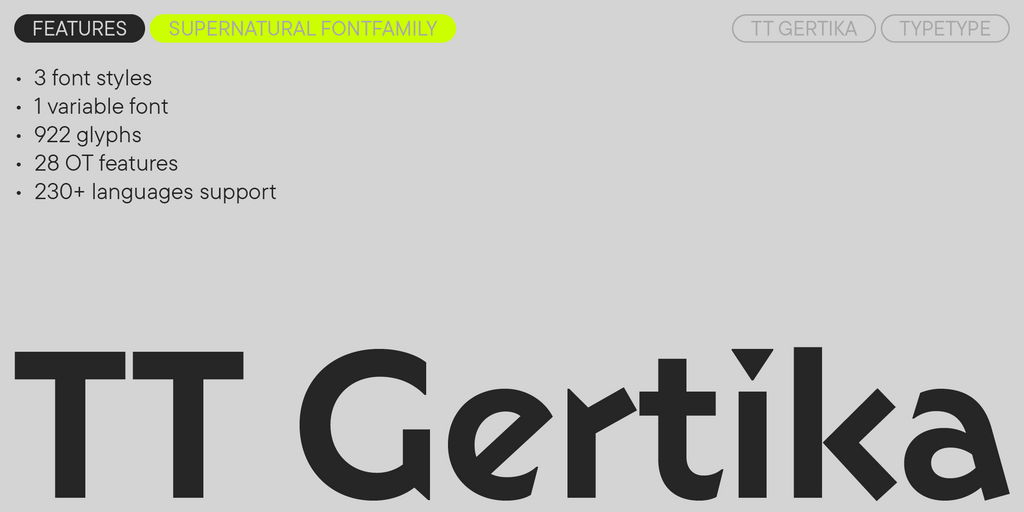
Минималистичные шрифты
TT Runs — это выразительный шрифт, который идеально впишется в проекты со спортивной тематикой. При этом гарнитура отлично подойдет и для других современных проектов: после обновления сфера ее применения значительно расширилась.
TT Turns — геометрический гротеск с акцентными круглыми знаками и выразительными нависающими элементами. Это универсальный шрифт, который лаконично выглядит и отлично читается в маленьком размере, при этом в крупных кеглях становится акцидентным и проявляет свой характер на максимум. Он энергичный, сильный и динамичный — особенно отчётливо это проявляется в наклонных начертаниях.
В TT Frantz можно найти небольшие отсылки в эстетике арт-деко, которые выражены в сильно заниженной или наоборот сильно завышенной талии у букв. Кроме того, в зависимости от положения ползунка регулировки оси, у некоторых букв изменяется закрытость апертуры.
TT Quaris — изысканная и современная ленточная антиква. Перед разработкой этой гарнитуры мы провели глубокое исследование архетипов ленточных антикв.
TT Modernoir — акцидентный гротеск с разноширинными пропорциями. Плавные линии и изящные формы ар-нуво в этом шрифте сочетаются с ритмичностью и импровизационной свободой джаза.
TT Firs Neue — скандинавский гротеск, сочетающий выразительные графические элементы с универсальностью использования. Мы проанализировали каждый контур и графический элемент. Пересобрали шрифт заново, чтобы сохранить лучшее и исправить необходимое.
TT Ramillas — стильная и современная антиква. Включает уникальные декоративные начертания и буквицы с цветочным орнаментом.
TT Paplane — акцидентный сквадраченный гротеск. Так, характерные черты этого гротеска — сквадраченные формы, 45-градусные срезы и обтекаемые внешние контуры.
TT Travels Next — сверхмодный широкий гротеск. Широкие пропорции — одна из отличительных черт этой гарнитуры: знаки почти не сужаются при переходе от толстого начертания к тонкому.
TT Firs Text создавался на основе обновленной в 2023 году гарнитуры TT Firs Neue. Мы сохранили эстетику скандинавского минимализма, но полностью перерисовали все выразительные элементы, сделав их более мягкими и традиционными.
TT Trailers — стильный и выразительный акцидентный гротеск. Его легко узнать по необычной графике: рисунок каждого знака в этом шрифте авторский, формы экспериментальные. Он гармонично смотрится в оформлении афиш и плакатов, идеально подходит для оформления титров. Однако на практике сфера применения этой гарнитуры гораздо шире.
TT Norms® Pro — один из самых востребованных шрифтов студии, выбор известных мировых брендов. Более трёх переизданий за семь лет, первые строчки на MyFonts, десятки кастомизаций. Это «рабочая лошадка», которая станет незаменимой базой любой шрифтовой коллекции.
TT Commons™ Pro — один из самых востребованных шрифтов студии. Сфера его применения практически безгранична! Беспроигрышный вариант для тех, кто ищет стильный и функциональный базовый шрифт для любых проектов.
TT Hoves Pro — скандинавский гротеск с нейтральным, но в то же время узнаваемым характером. Это удобный и функциональный, при этом стильный и эстетичный инструмент для дизайнеров. Такой шрифт позволит вам решать множество разноплановых задач!
TT Supermolot Neue — непобедимое оружие в борьбе за стиль! Это технологичный модульный гротеск с футуристическим настроением и мощным функционалом. Шрифт идеально подойдёт для оформления компьютерных игр и множества других проектов.
TT Firs Neue — сбалансированный гротеск со скандинавскими мотивами. Это выразительный и привлекательный, при этом лаконичный и универсальный в использовании шрифт. Переиздан дважды, чтобы быть безупречным.
TT Rounds Neue — мягкий и дружелюбный шрифт, который умеет быть разным. В тонких начертаниях он выглядит минималистично и нейтрально. В жирных же — «надувается» и округляется, приобретая инфантильные черты.
TT Fors — тот самый шрифт «для всего». Это стильный, лаконичный и функциональный геометрический гротеск с выверенными формами. Его можно использовать и в интерфейсах, и для создания акцентов.
TT Geekette — вариативная антиква с дружелюбным характером. Мы ушли от упрощений сухой геометрии и поэкспериментировали с плавностью, мягкостью и пластичностью форм. А чтобы шрифт стал чуть более стильным и серьёзным, мы сделали его моноширинным.
TT Alientz является вариативным шрифтом, который позволяет пользователю совершить визуальное путешествие от лаконичного инопланетного гротеска к сверх акцидентной и очень колючей антикве.